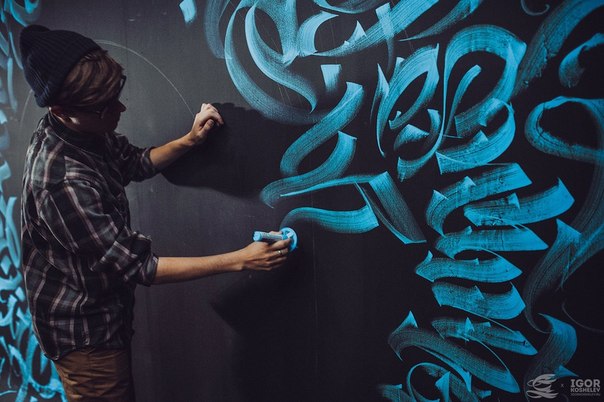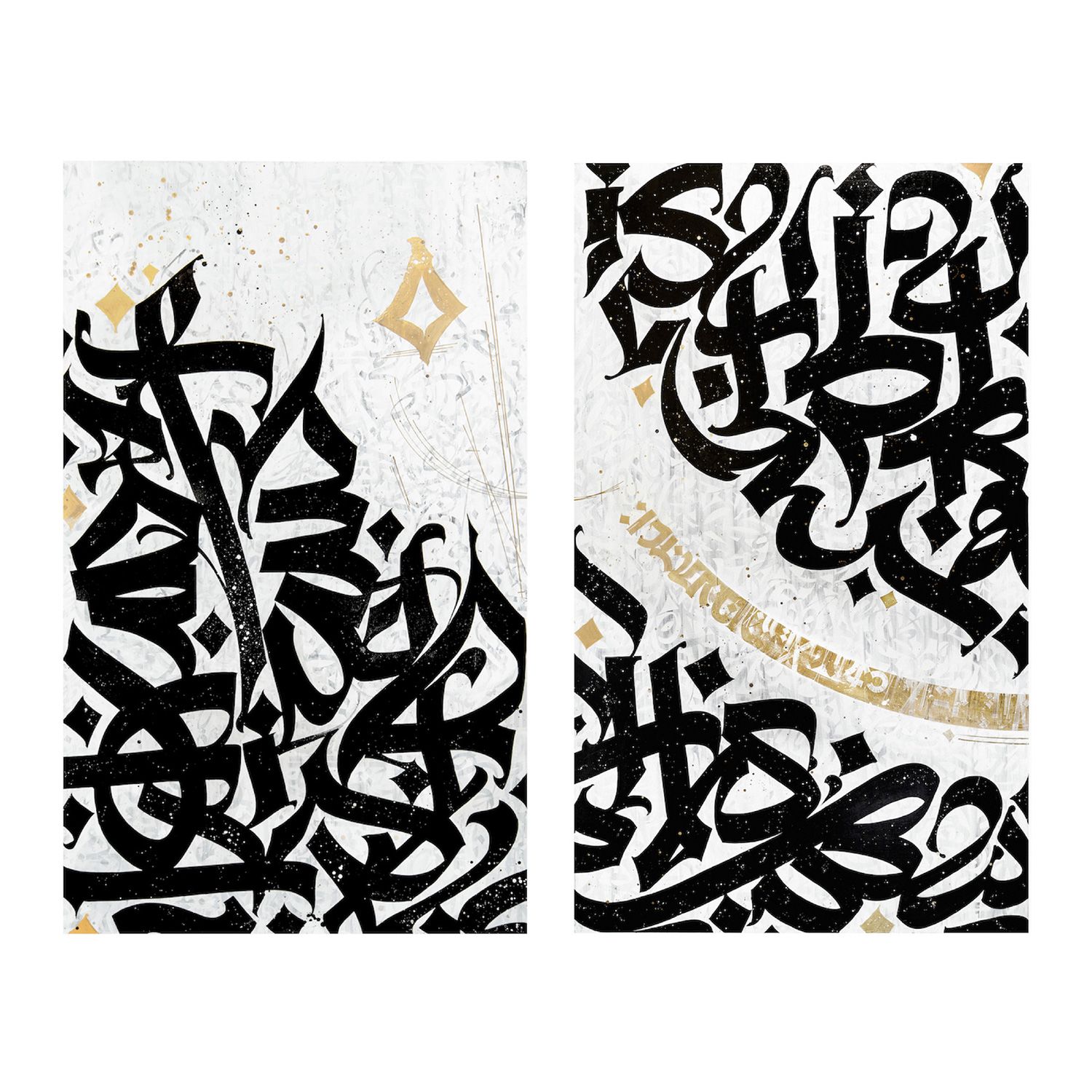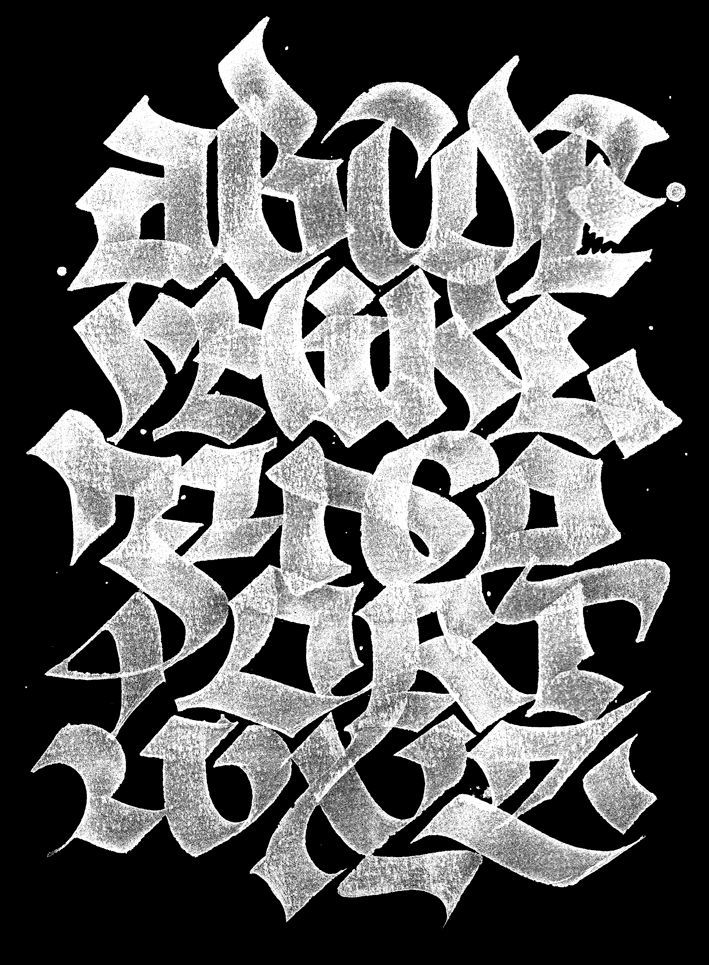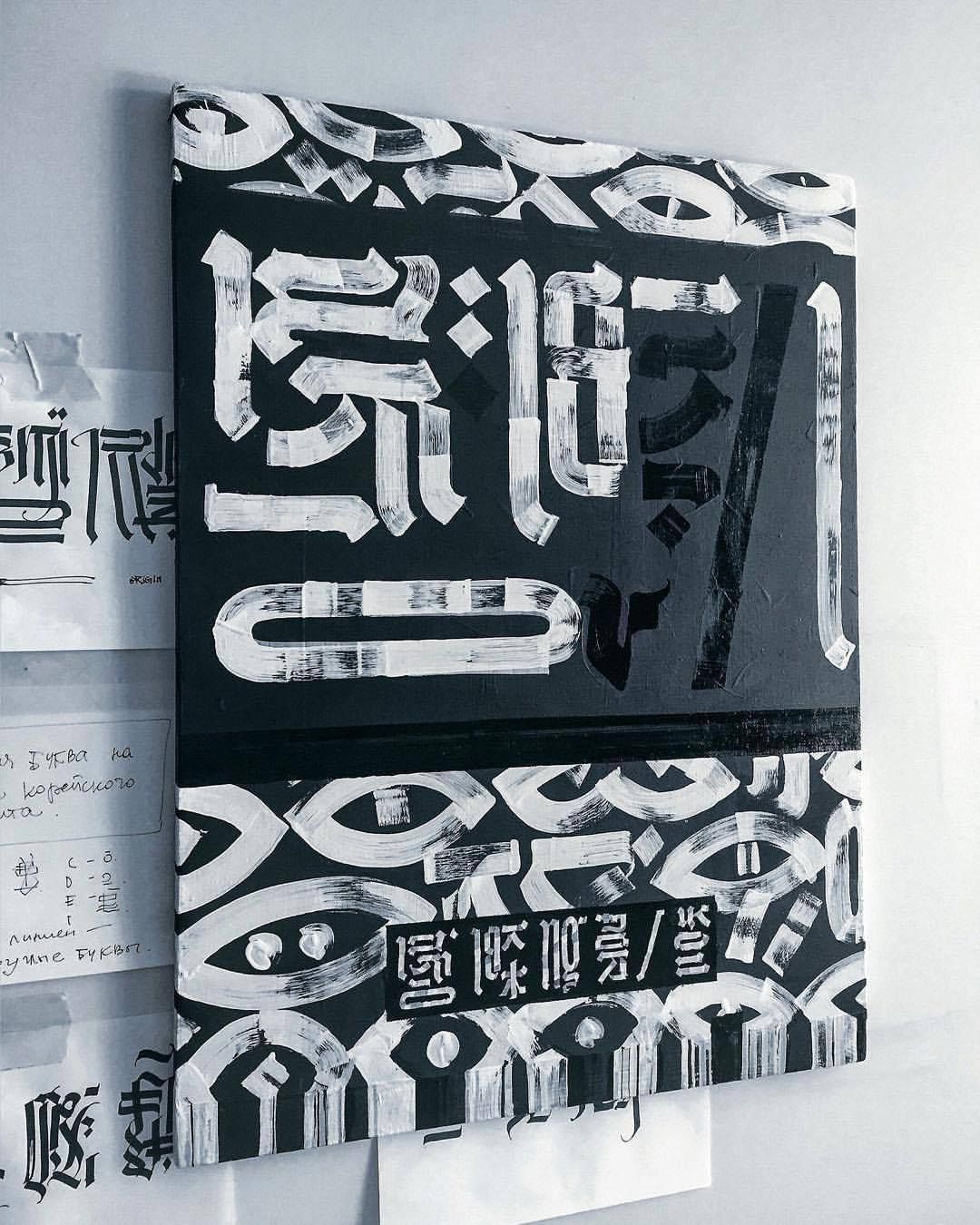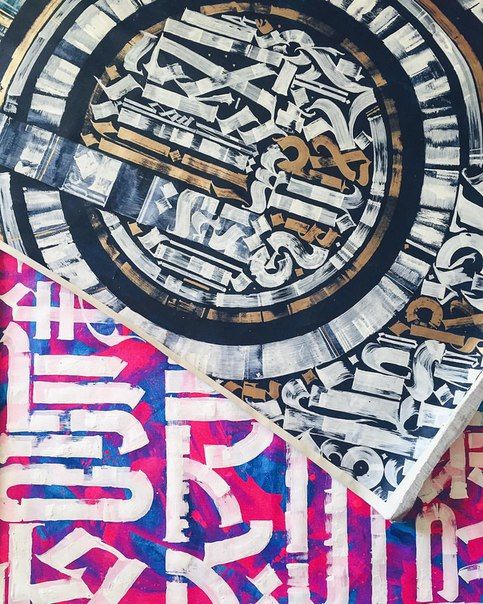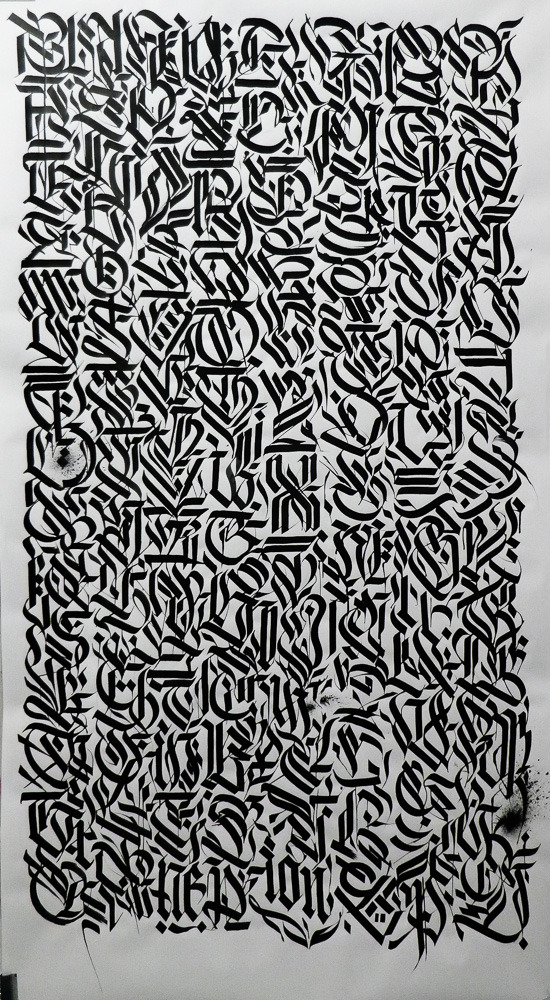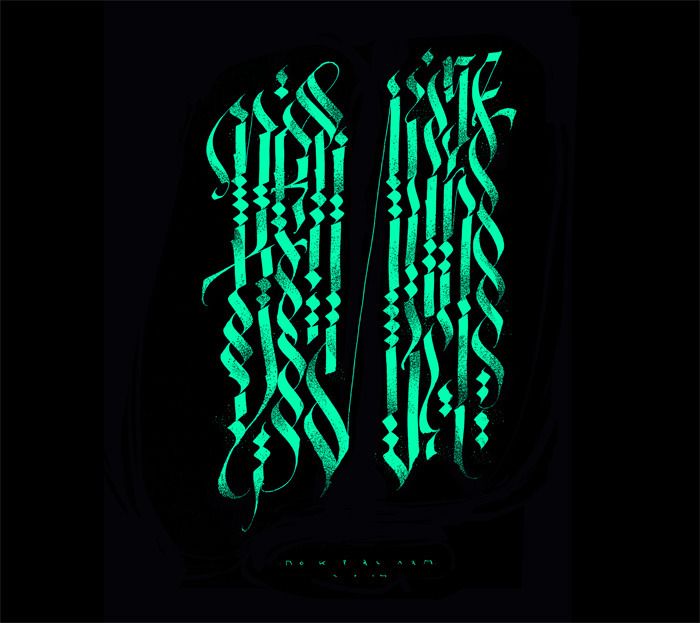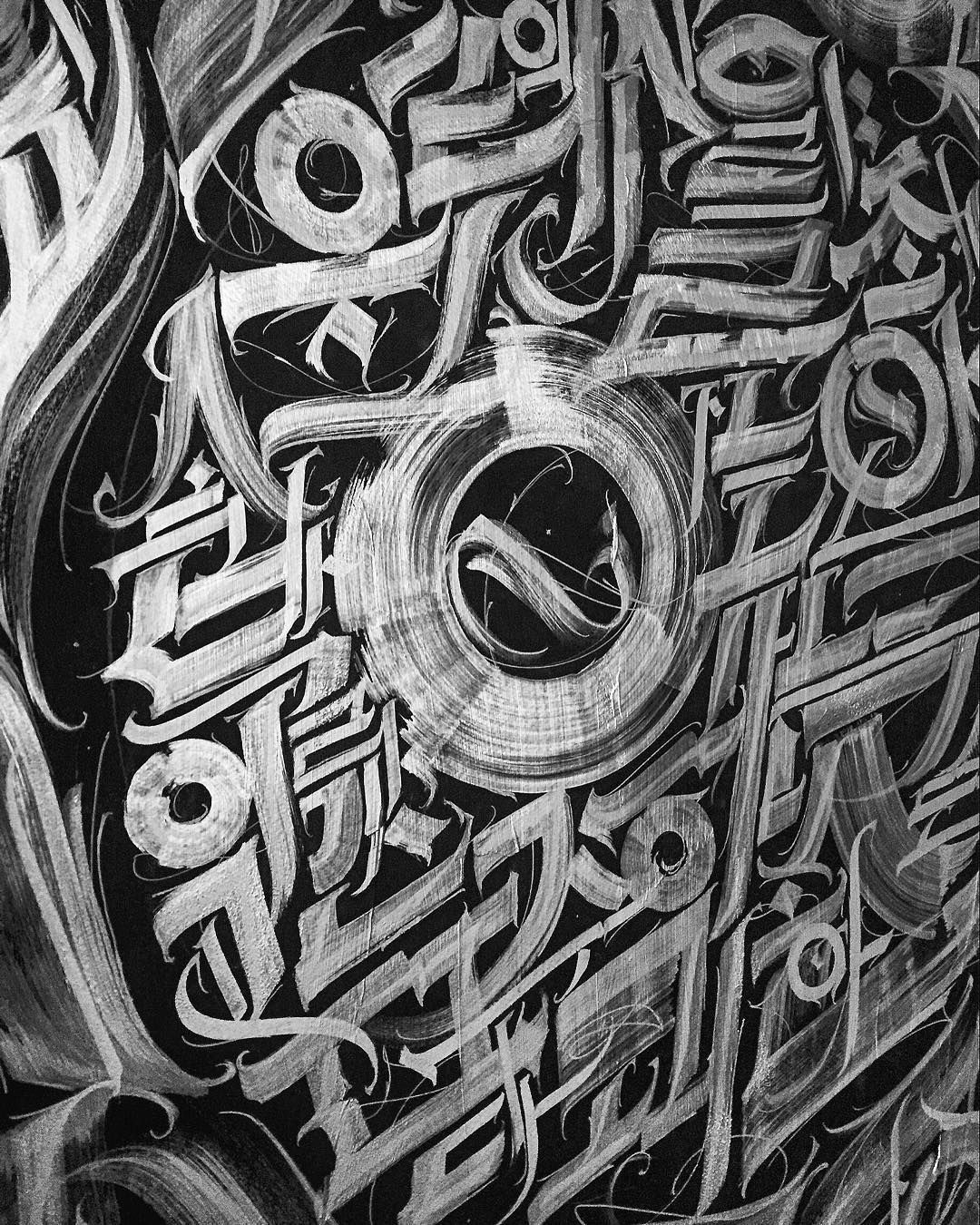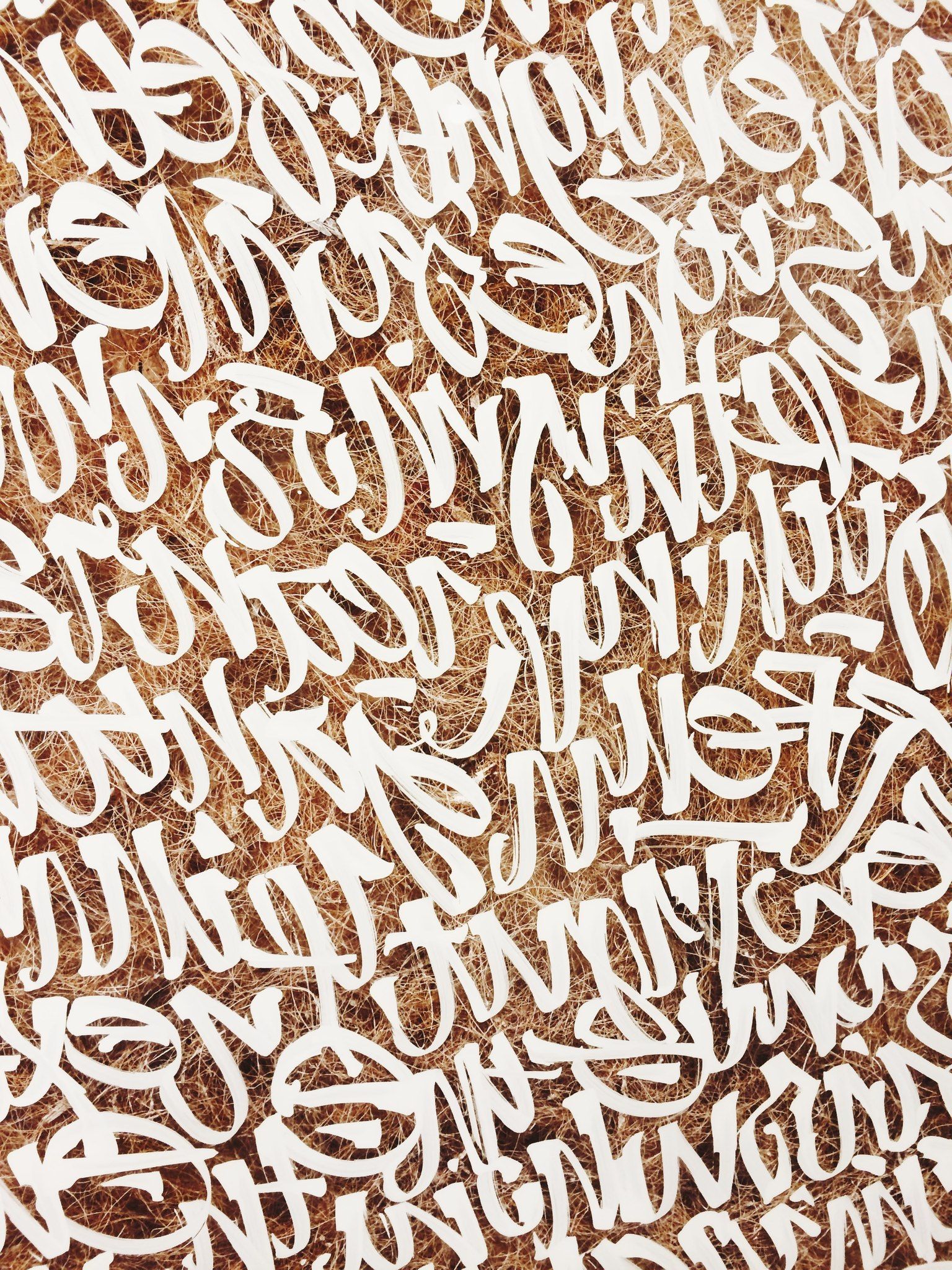
«Чтобы создать что-то новое, нужно много экспериментов»
Современная каллиграфия глазами Покраса Лампаса
Если вы интересуетесь дизайном и современной каллиграфией, то наверняка вас можно было встретить 19-20 августа в «Пери Инновации». В течение двух дней известный российский дизайнер и каллиграф Покрас Лампас, он же Арсений, на территории бизнес-инкубатора провел два занятия — теоретическое и практическое.
В первый день художник рассказывал о тенденциях в современном искусстве и дизайне на примере различных авторских коммерческих и арт-проектов, ну а во второй уже на практике познакомил участников воркшопа с самыми популярными каллиграфическими инструментами и основами работы с ними для самостоятельной практики.
На протяжении 7 лет Покрас Лампас экспериментирует с возможностями шрифтов: как было написано на одном из российских порталов: «его стиль сочетает брутальность граффити с разнообразием используемых форм, цветов и инструментов, а также стремлением к большим масштабам».
— Да, я бывал в близлежащих регионах ─ в Краснодарском крае, Ставрополье, а сюда как-то не хотелось заезжать, и это даже не в силу стереотипа о Дагестане. Тут, по моему мнению, очень мало проходит вещей, связанных с дизайном и каллиграфией, не проходит мероприятий такого уровня, как, например, в соседнем Краснодаре.
— Ну, в общем-то да. Я считал, какой смысл рассказывать людям то, что им не интересно. Но в этот раз я получил приглашение от «Пери инновации», касающееся конкретного мастер-класса по каллиграфии, меня это в какой-то степени порадовало, значит, движение в этом направлении тут появилось.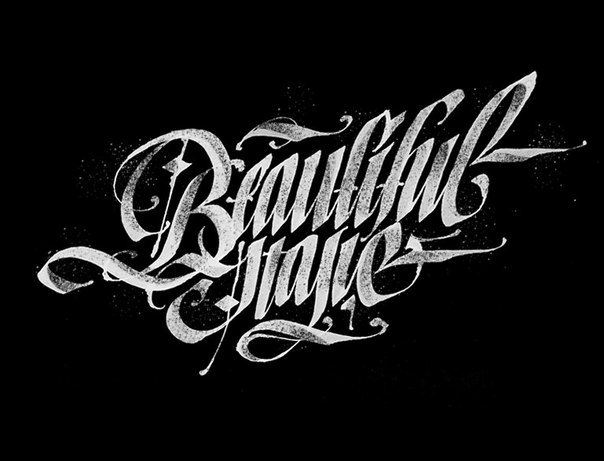
— Давай поговорим о твоей работе, мы присутствовали на воркшопе, и в процессе общения с аудиторией ты упомянул, что у тебя нет художественного образования.
Откуда тогда появился интерес к каллиграфии, шрифтам, и как вообще начался твой творческий процесс. Ты, кажется, вначале занимался граффити?
— Совершенно верно. Все на самом деле взаимосвязано, у меня нет базы и академических знаний, я вообще не умел рисовать ни людей, ни персонажей. Но при этом мне хотелось заниматься такого рода творчеством, и я попробовал для начала себя в граффити, где ты сам выбираешь, что рисовать — либо персонажей, либо шрифты. Я понимал, что кроме шрифтов мне вряд ли что-то удастся, и я стал больше узнавать о построении букв, об инструментах в каллиграфии, то есть сам начал изучать базовые вещи. На момент, когда я стал заниматься каллиграфией, я был уже достаточно популярным в граффити, меня приглашали на различные фестивали в Москве и по России.
Занимаясь граффити, ты постоянно изучаешь шрифты, работаешь над механикой, начинаются моменты изучения строения графических и композиционных основ. И когда я стал заниматься каллиграфией, то уже понимал, что нужно брать в руки и как это нужно писать.
Я даже в тот момент не читал специальных книг, больше писал так, как вижу. Да, порой это были совсем неправильные вещи, но я на них тренировался и со временем стал в этом расти и развиваться.
— Слушая тебя, возникает встречный вопрос про образование, на мастер-классе ты также поделился, что как таковое образование не нужно, но ведь самообразование получается наоборот необходимо?
— Конечно, человек в этом случае не столько выбирает, чем ему заниматься, а находится в состоянии, когда для собственного развития появляется необходимость получить знания самому, иначе никак не будешь двигаться дальше. Дизайну, по сути, мало кто учится в университете. Часто вообще при обучении педагоги бракуют хорошие и талантливые работы, я сам лично был свидетелем, как моим знакомым ребятам за хорошие проекты ставили плохие оценки или вообще не принимали, говоря, что это плохо, что всё сделано неправильно и надо по старинке.
— То есть идет навязывание своего мнения, но не развитие личности?
— Очень сильное навязывание и порой совсем некорректное.
На самом деле это очень неправильное отношение к студентам, лично мне кажется, причина кроется в том, что преподаватели получают довольно низкую заработную ставку, и у них самих нет мотивации развиваться и еще при этом кого-то там поддерживать. Это очень печально на самом деле. С такими людьми сложно найти общий язык, получается, что ты должен либо во всем с ними соглашаться, не идти на конфликт, и тогда какой бы у тебя ни был уровень работ, ты будешь нормально оценен. Либо ты идешь на конфликт, споришь, потому что твое видение, по сути, более правильное, но тогда тебе будут занижать оценки. В итоге это очень жесткая трата времени, учитывая и тот факт, что образование предполагает и другие предметы по дисциплине, не связанные с образованием, которое ты пришел получать.